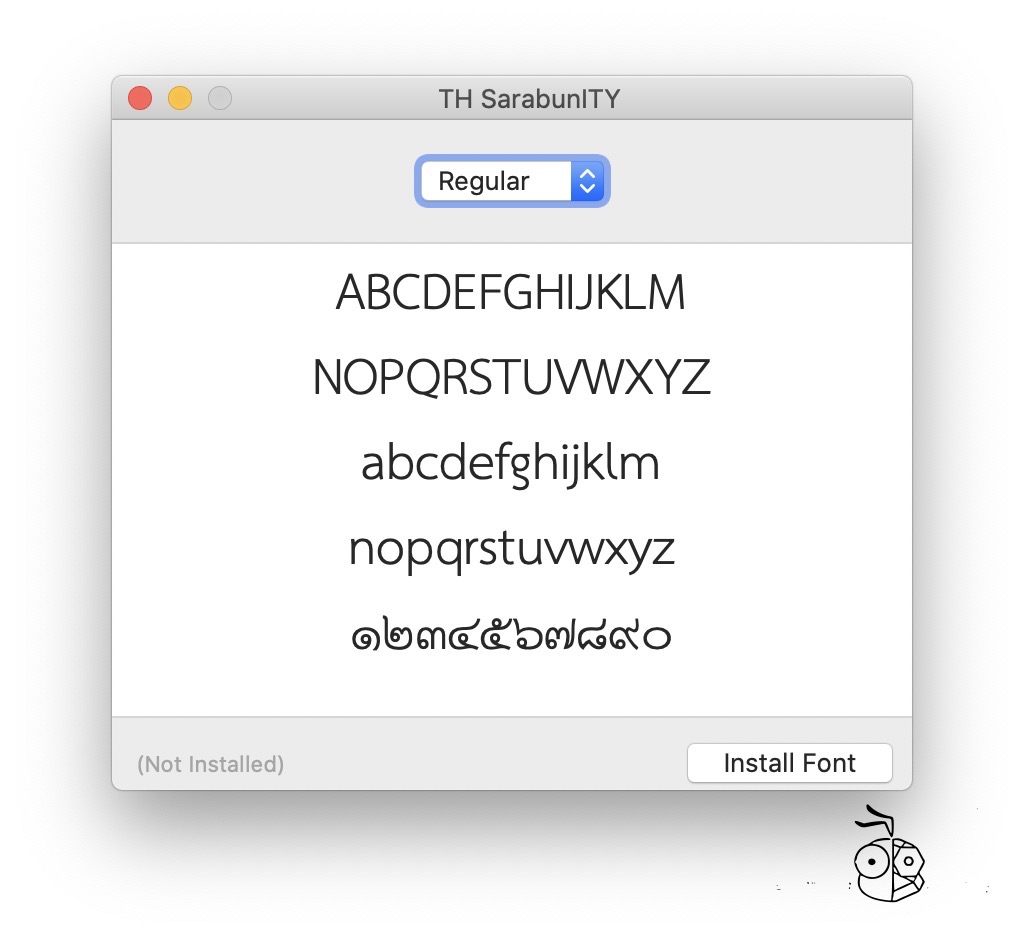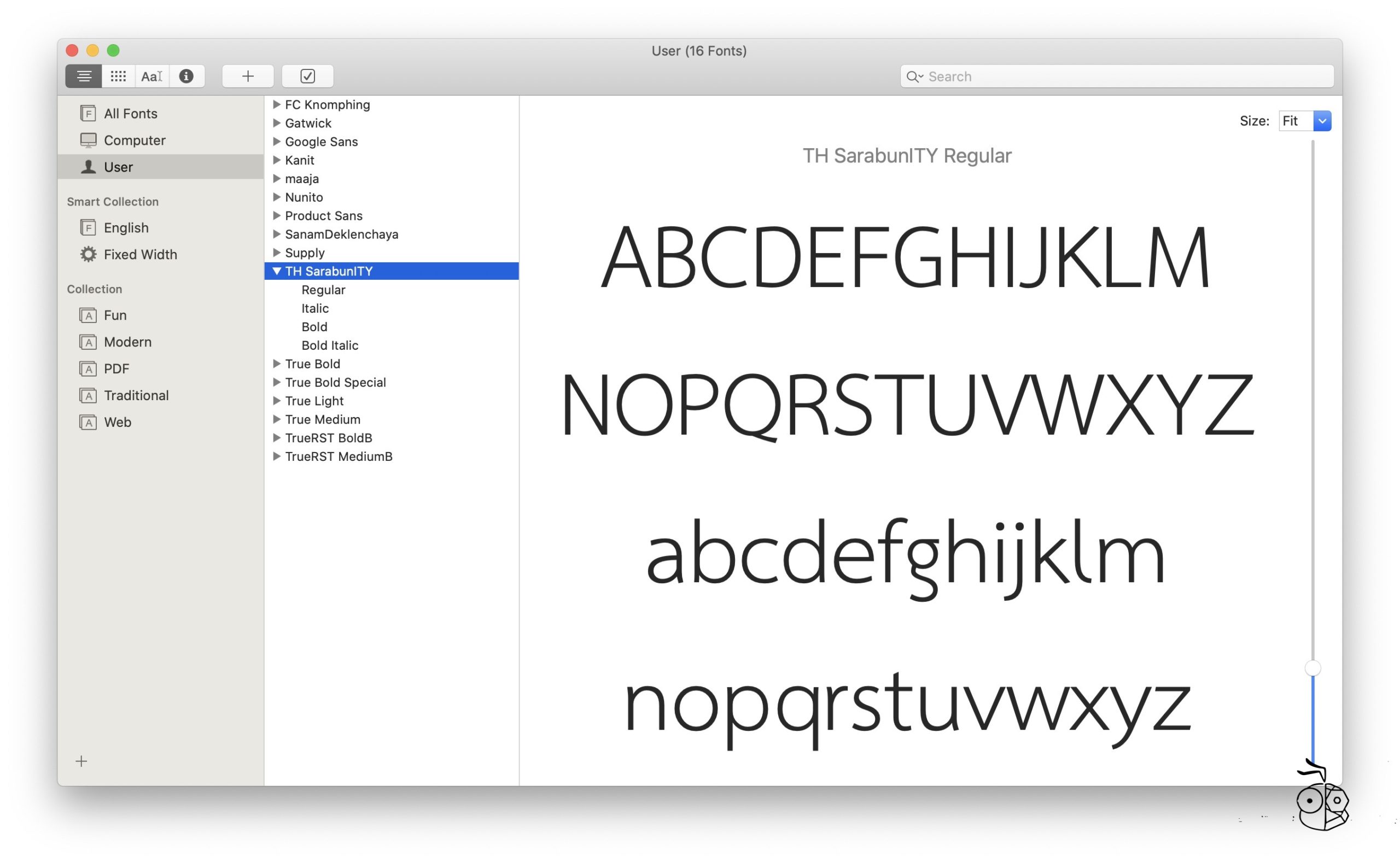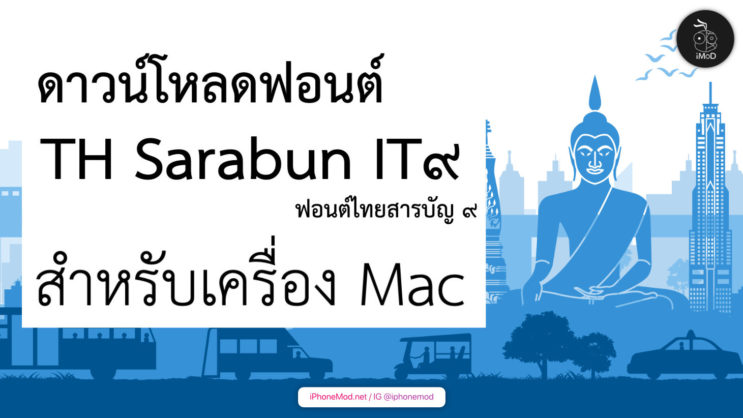
หากท่านใดต้องการฟอนต์ TH Sarabun IT๙ (IT9) เพื่อพิมพ์และแก้ไขเอกสารไฟล์ .doc ของ MS Office บนเครื่อง Mac สามารถดาวน์โหลดไฟล์ฟอนต์เพื่อนำไปติดตั้งได้ที่นี่ ซึ่งหากติดตั้งไฟล์ฟอนต์ต้นฉบับจะไม่สามารถติดตั้งได้ดังนั้นทีมงานจึงได้ปรับแต่งฟอนต์ดังกล่าวเพื่อให้สามารถใช้งานบนเครื่อง Mac ได้
แม้ว่าฟอนต์ TH Saranbun IT๙ จะไม่เป็นที่นิยมและเริ่มถูกยกเลิกการใช้งานออกไปแล้ว แต่ก็ยังมีบางหน่วยงานนั้นเลือกใช้ฟอนต์นี้เป็นมาตรฐานของการทำงานเอกสารอยู่ (ลองค้นหาข้อมูลกันดูนะว่าเพราะอะไร) แต่เอาเป็นว่า ที่มีของปัญหานี้คือ ผู้ใช้งาน Mac ไม่ว่าเป็น MacBook, iMac, Mac Pro ฯลฯ หากมีความจำเป็นต้องใช้ฟอนต์ TH Sarabun IT๙ บนเครื่อง Mac แล้วหละก็ ทีมงานได้ปรับปุรงไฟล์ให้แล้วเพื่อให้สามารถใช้งานบนเครื่อง Mac ได้
อยากเรียนไปยังหน่วยงานที่ยังบังคับให้ใช้ฟอนต์ TH Saranbun IT๙ อยู่
ควรยกเลิกแล้วหันไปใช้ฟอนต์อื่นอย่าง TH Saranbun PSK แทน
จะได้ไม่เป็นภาระของระบบคอมพิวเตอร์และภาระของผู้ที่ต้องเขียนหรือแก้ไขรายงาน